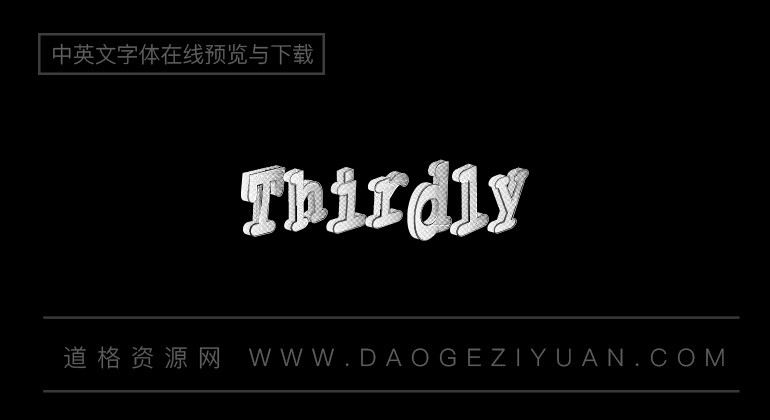
Thirdly是一款字体,由英国设计师Pete Lacey设计,是一款现代活泼的字体,拥有清晰的线条和细节,搭配色彩丰富的活泼灵动的字体,可以提供丰富的表情,可以在海报、标志、广告、网页等多种设计中使用。它具有极高的可读性,可以提供清晰的文字,帮助提升设计的质量。内容介绍
Thirdly是一款非常不错的手写艺术字体,具有很好的视觉感,适合于文化类的宣传设计、商业类品牌的广告和产品包装设计以及个性化文字排版等较多场景。